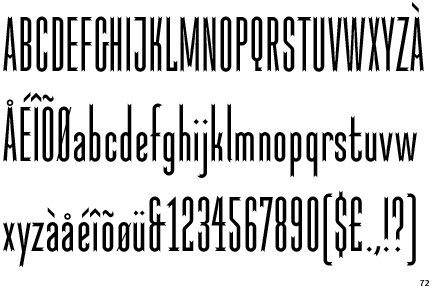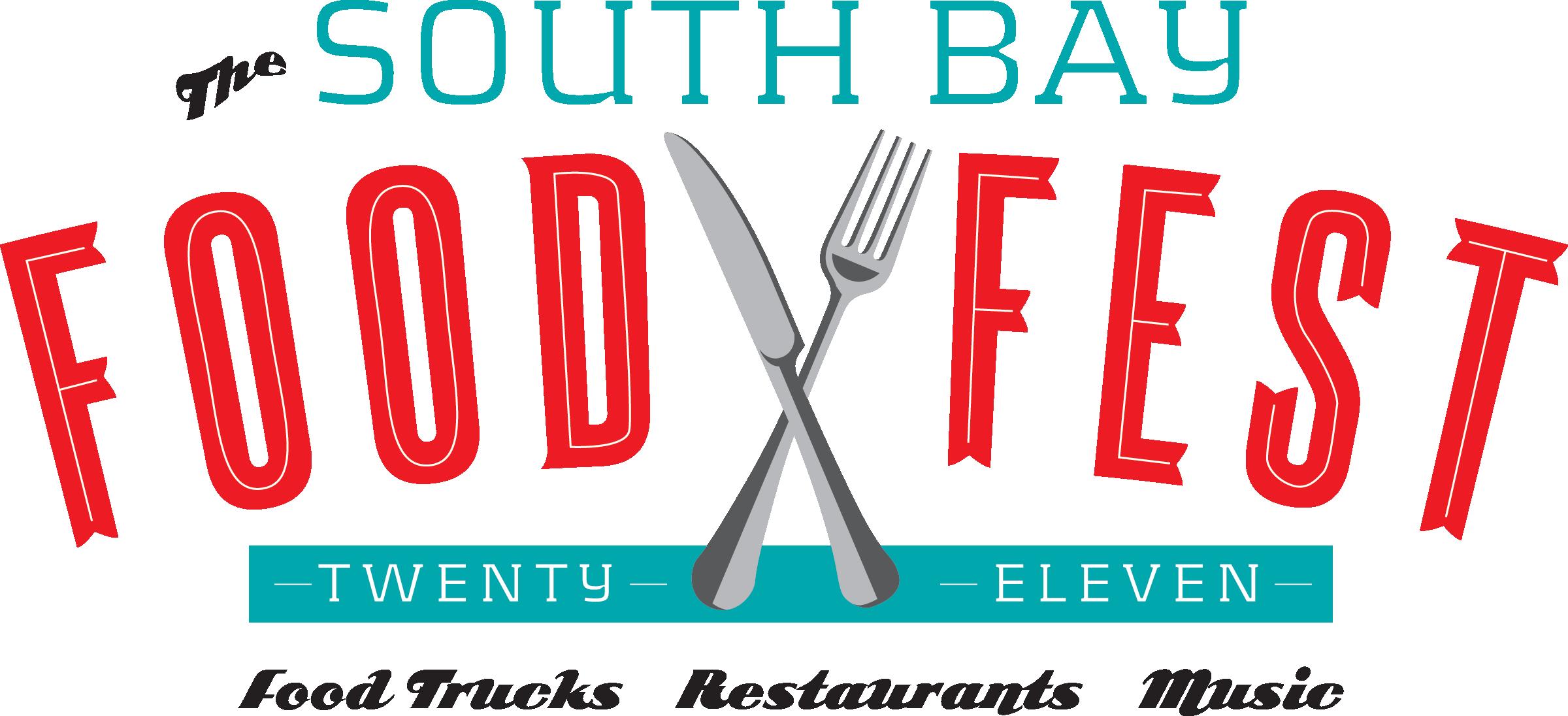
Schrift gesucht! (Food Fest)
ich suche dringend eine Schrift, leider habe ich nur einen Screenshot.
Kann mir bitte da einer weiterhelfen?
Hier etwas größer …
etwas näher drann ist die Station Two:
Bei der Buchstabenform ohne Inline denke ich an die ITC Malstock:
ITC Malstock
Based on a signpost lettering produced with a flat brush, and using a long bar called a Maalssok as a rest for the painter's hand.
Designer: František Štorm
Year: 1996
Die Schrift würde ganz gut passen, aber es gibt von der ITC Malstock nach meinen Kenntnissen keine Inline und auch keine passende Laufweite/Dicke. Möglicherweise wurde aber auch eine ganz normale, hochkondensierte Sans, so was wie eine Poster Sans oder Triple Condensed Sans, von Hand modifiziert? Die Inline im großen O und das große D sehen etwas danach aus?